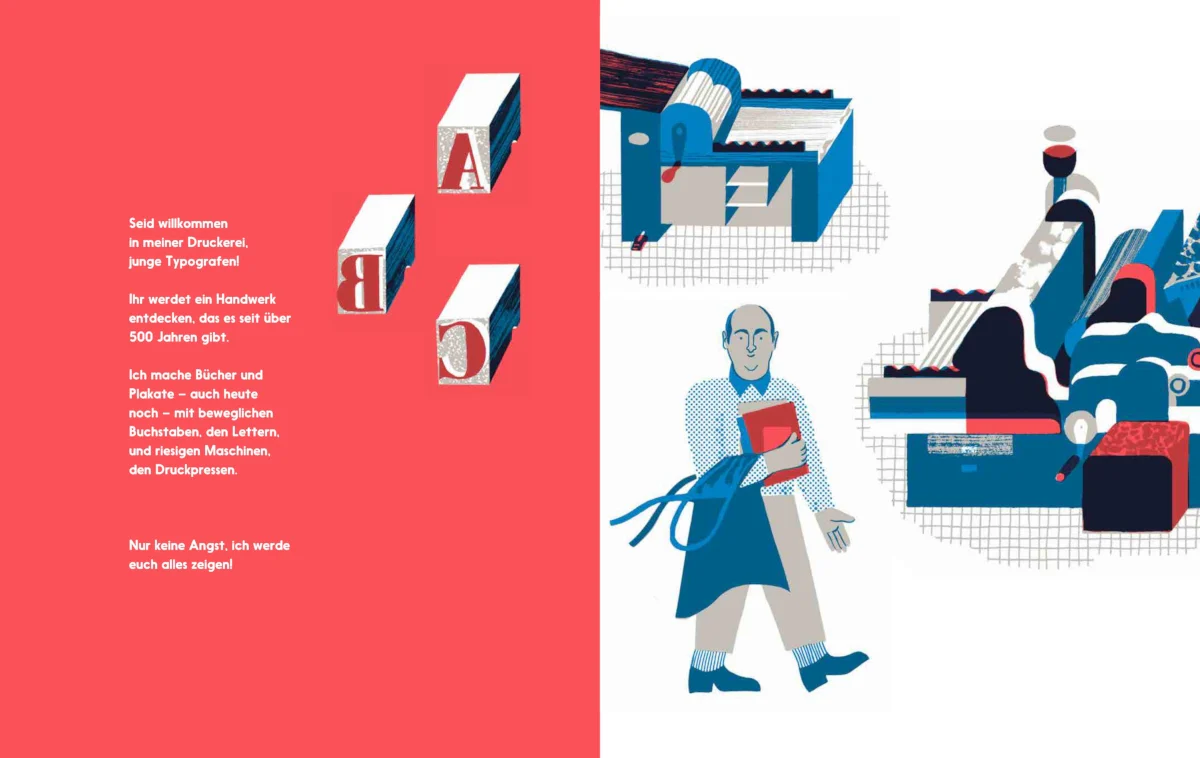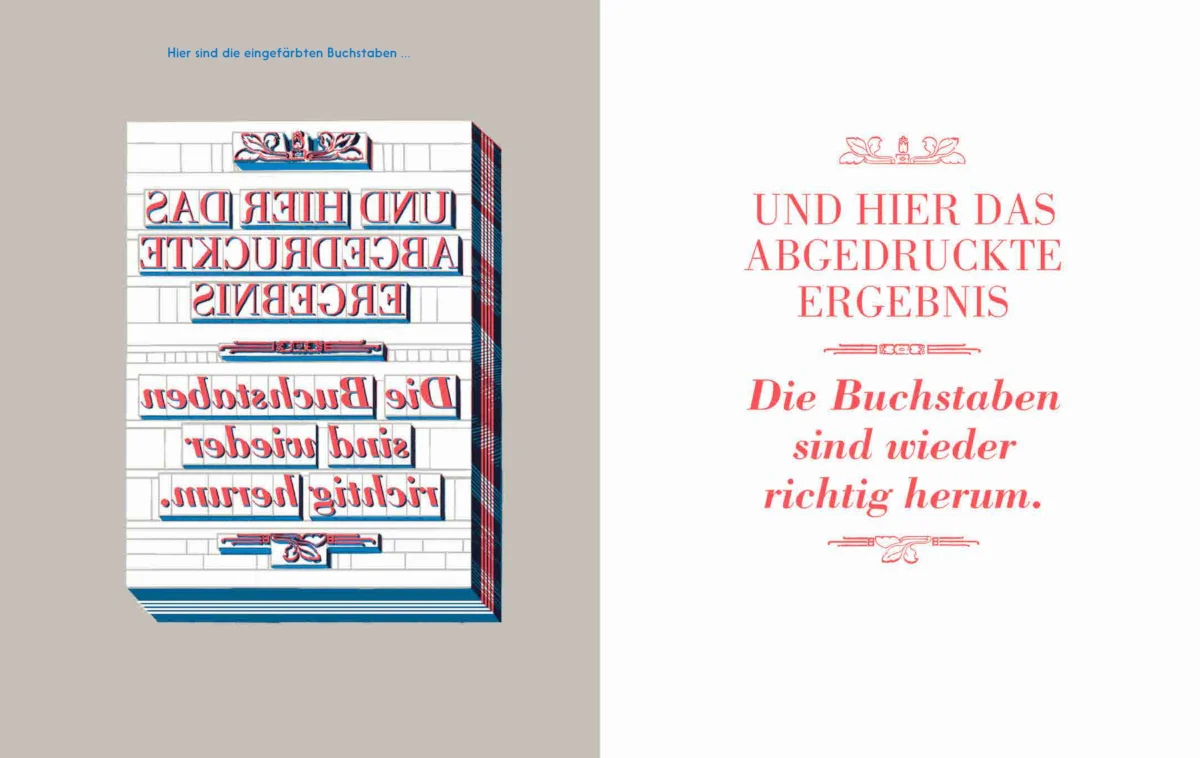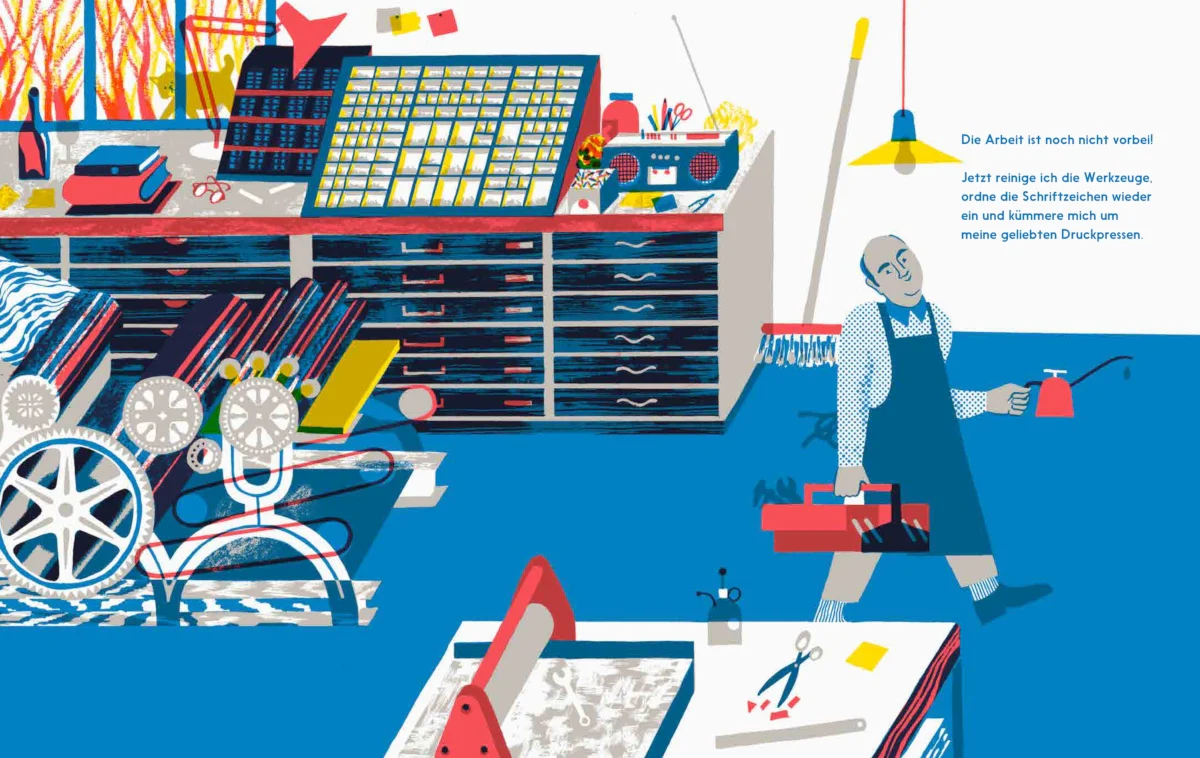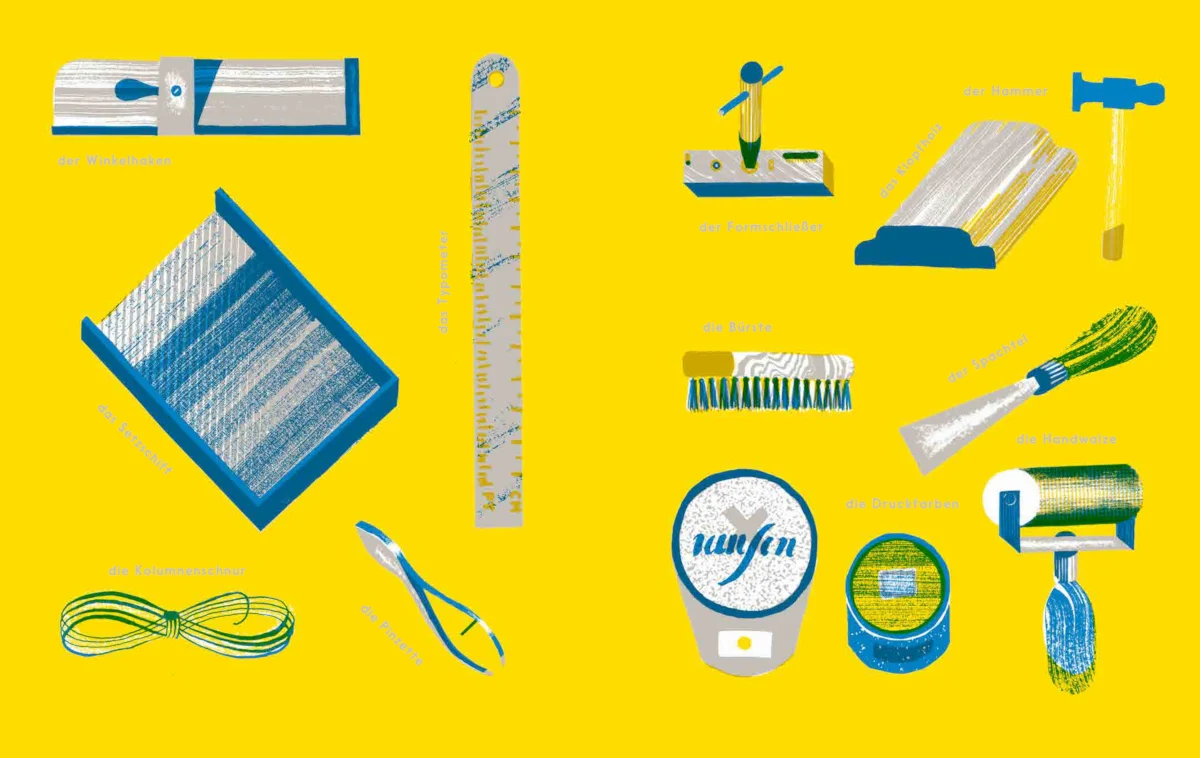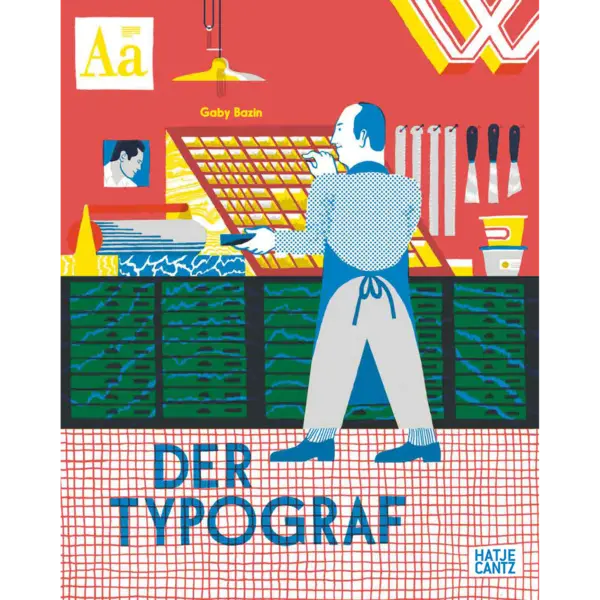
In diesem Buch für Kinder ab 6 Jahren führt die französische Illustratorin Gaby Bazin in die Welt des Schriftsatzes und Drucks mit beweglichen Lettern ein. Zuvor wurde das Konzept bereits mit dem Thema und Titel »Die Lithografin« umgesetzt. Die nun nachgelegte Typografie-Version verfügt über 40 Seiten und spannt den Bogen von der Entstehung der Schrift, über die Erfindung des Buchdrucks, bis hin zur konkreten Umsetzung am Beispiel des Satzes und Drucks einer Spalte an einer Abziehpresse.
Die Wissensvermittlung erfolgt kindgerecht in einem eigenständigen und charmanten Stil aus Handzeichnungen. Dabei wird aber durchaus nicht auf Fachbegriffe der Typografie und Druckbranche verzichtet. Wo nötig wurden die Grafiken des in mehreren Sprachen erschienenen Buches auch alle passend für den deutschen Sprache umgesetzt. So wird etwa der hierzulande übliche, deutsche Setzkasten dargestellt und nicht etwa der französische. Den französischen Titel »Le Typographe« mit »Der Typograf« zu übersetzen, ist nachvollziehbar, passt aber streng genommen nicht hundertprozentig. Im Deutschen haben Typograf und Typografie etwas andere Definitionen als in romanischen Sprachen. Immerhin verweist die Beschreibung auf der Rückseite des Buches dann aber schon wieder auf »Schriftsetzer und Drucker« als die tatsächlich im Buch dargestellten und erklärten Tätigkeiten.
Alles in allem ein äußerst charmanter Einstieg in die Welt des Drucks mit beweglichen Lettern – ideal als Geschenkbuch für Kinder, Jugendliche und womöglich sogar Erwachsene, die an der illustrativen Darstellung echten Fachwissens Freude finden können.